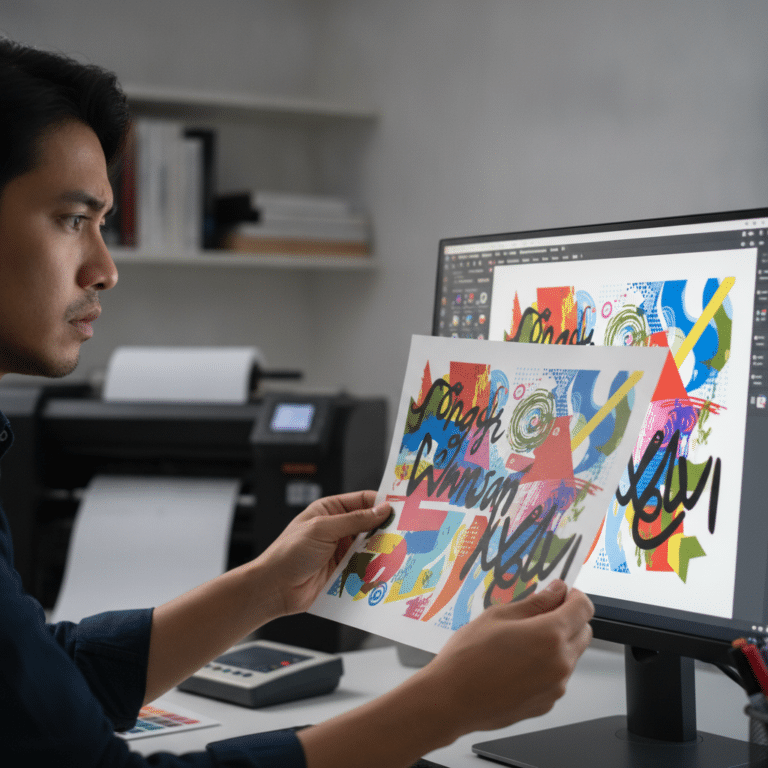
เคล็ดลับเลือกฟอนต์ป้ายโฆษณาให้อ่านง่าย ดึงดูดลูกค้า
การเลือกรูปแบบตัวอักษรหรือฟอนต์สำหรับป้ายโฆษณาเป็นองค์ประกอบที่สำคัญอย่างยิ่งในการสื่อสารกับผู้บริโภค ฟอนต์ที่เหมาะสมไม่เพียงแต่ช่วยให้ข้อความอ่านง่ายและชัดเจน แต่ยังมีบทบาทในการสร้างการรับรู้แบรนด์และดึงดูดความสนใจของลูกค้าเป้าหมาย การตัดสินใจเลือกฟอนต์จึงควรผ่านการพิจารณาอย่างรอบคอบ เพื่อให้ป้ายโฆษณาสามารถทำหน้าที่ได้อย่างเต็มประสิทธิภาพ
สรุปประเด็นสำคัญสำหรับการเลือกฟอนต์
- ความชัดเจนคือหัวใจหลัก: เลือกฟอนต์ที่อ่านง่ายจากระยะไกลและในเวลาอันสั้น โดยเฉพาะฟอนต์ประเภท Sans Serif ที่มีความหนาพอเหมาะ
- จำกัดจำนวนฟอนต์: การใช้ฟอนต์มากเกินไปบนป้ายเดียวทำให้ดูรกและไม่เป็นมืออาชีพ ควรใช้เพียง 1-2 รูปแบบที่เข้ากันได้ดี
- ขนาดมีความสำคัญ: ขนาดของตัวอักษรต้องสัมพันธ์กับระยะการมองเห็น เพื่อให้ผู้ที่สัญจรผ่านไปมาสามารถอ่านข้อมูลสำคัญได้ทันที
- สร้างลำดับชั้นทางสายตา: ใช้ขนาด ความหนา และสีของฟอนต์เพื่อจัดลำดับความสำคัญของข้อมูล ดึงดูดสายตาไปยังหัวข้อหลักก่อน แล้วจึงตามด้วยรายละเอียด
- สอดคล้องกับบุคลิกแบรนด์: ฟอนต์ที่เลือกใช้ควรสะท้อนถึงตัวตนและภาพลักษณ์ของธุรกิจ เพื่อสร้างการจดจำและความน่าเชื่อถือในระยะยาว
สำหรับผู้ประกอบการธุรกิจขนาดกลางและขนาดย่อม (SME) การทำความเข้าใจเกี่ยวกับเคล็ดลับเลือกฟอนต์ป้ายโฆษณาให้อ่านง่าย ดึงดูดลูกค้า ถือเป็นกุญแจสำคัญในการสร้างความได้เปรียบทางการแข่งขัน ป้ายโฆษณาหน้าร้านหรือป้ายไวนิลที่ออกแบบมาอย่างดีสามารถเป็นเครื่องมือทางการตลาดที่ทรงพลัง ทำหน้าที่เชิญชวนลูกค้าให้เข้ามาใช้บริการได้ตลอด 24 ชั่วโมง การเลือกฟอนต์จึงไม่ใช่แค่เรื่องของความสวยงาม แต่เป็นศาสตร์และศิลป์ที่ส่งผลโดยตรงต่อการตัดสินใจซื้อและความสำเร็จของธุรกิจ
บทความนี้จะนำเสนอแนวทางและเทคนิคเชิงลึกในการเลือกฟอนต์สำหรับสื่อสิ่งพิมพ์ประเภทป้ายโฆษณา ตั้งแต่ความสำคัญของฟอนต์ต่อภาพลักษณ์แบรนด์ หลักการเลือกประเภทฟอนต์ที่เหมาะสม ไปจนถึงเทคนิคการจัดวางองค์ประกอบเพื่อให้เกิดประสิทธิภาพสูงสุดในการสื่อสาร ซึ่งจะเป็นประโยชน์ต่อเจ้าของธุรกิจ นักการตลาด และนักออกแบบที่ต้องการสร้างสรรค์ป้ายโฆษณาที่โดดเด่นและบรรลุวัตถุประสงค์ทางการตลาด
ความสำคัญของฟอนต์ต่อการรับรู้แบรนด์
ฟอนต์หรือไทโปกราฟี (Typography) เป็นมากกว่าแค่ตัวอักษรที่เรียงต่อกันเป็นคำ แต่เป็นองค์ประกอบสำคัญในการสร้างอัตลักษณ์ของแบรนด์ (Brand Identity) ในโลกที่เต็มไปด้วยข้อมูลข่าวสาร การมีภาพลักษณ์ที่ชัดเจนและน่าจดจำคือสิ่งจำเป็น ฟอนต์ที่ถูกเลือกอย่างพิถีพิถันจะกลายเป็นเสียงและบุคลิกของแบรนด์ที่สื่อสารกับลูกค้าได้โดยไม่ต้องเอ่ยคำพูด
สร้างการจดจำและความน่าเชื่อถือ
เมื่อผู้บริโภคเห็นฟอนต์ที่ใช้เป็นประจำในทุกสื่อของแบรนด์ ไม่ว่าจะเป็นบนป้ายโฆษณา นามบัตร หรือเว็บไซต์ จะเกิดการเชื่อมโยงและการจดจำโดยไม่รู้ตัว ฟอนต์ที่ดูเป็นมืออาชีพ สะอาดตา และเหมาะสมกับประเภทธุรกิจ จะช่วยเสริมสร้างความน่าเชื่อถือและความไว้วางใจให้กับลูกค้าได้เป็นอย่างดี ในทางกลับกัน ฟอนต์ที่อ่านยากหรือไม่สอดคล้องกับภาพลักษณ์ อาจสร้างความรู้สึกสับสนและลดทอนความเชื่อมั่นที่มีต่อแบรนด์
สื่อสารบุคลิกของแบรนด์
ฟอนต์แต่ละรูปแบบมีลักษณะเฉพาะตัวที่สามารถกระตุ้นอารมณ์และความรู้สึกที่แตกต่างกันได้ ตัวอย่างเช่น:
- ฟอนต์ที่มีความหนาและแข็งแรง อาจสื่อถึงความมั่นคง ความน่าเชื่อถือ เหมาะสำหรับธุรกิจการเงินหรือก่อสร้าง
- ฟอนต์ที่ดูโค้งมนและเป็นมิตร อาจสื่อถึงความอ่อนโยน การเข้าถึงง่าย เหมาะสำหรับสินค้าสำหรับเด็กหรือธุรกิจบริการ
- ฟอนต์ที่ดูหรูหราและมีเชิง (Serif) อาจสื่อถึงความคลาสสิก ประสบการณ์ที่ยาวนาน เหมาะสำหรับแบรนด์สินค้าลักซ์ชัวรีหรือธุรกิจที่มีประวัติศาสตร์
การเลือกฟอนต์ที่สอดคล้องกับบุคลิกของแบรนด์จึงเป็นการตอกย้ำจุดยืนและคุณค่าของธุรกิจให้ชัดเจนยิ่งขึ้น
หลักการพื้นฐานในการเลือกฟอนต์สำหรับป้ายโฆษณา
การออกแบบป้ายโฆษณาที่มีประสิทธิภาพต้องยึดหลักความเรียบง่ายและชัดเจนเป็นสำคัญ การเลือกฟอนต์ก็เช่นเดียวกัน การทำความเข้าใจหลักการพื้นฐานจะช่วยให้การตัดสินใจง่ายขึ้นและได้ผลลัพธ์ที่ดี
จำกัดจำนวนฟอนต์: น้อยแต่มาก
หนึ่งในข้อผิดพลาดที่พบบ่อยที่สุดในการออกแบบป้ายหน้าร้านคือการใช้ฟอนต์หลากหลายรูปแบบมากเกินไป ซึ่งทำให้ป้ายดูสับสน ขาดความเป็นเอกภาพ และลดทอนความเป็นมืออาชีพ แนวทางปฏิบัติที่ดีที่สุดคือการจำกัดการใช้ฟอนต์ไว้ที่ 1-2 รูปแบบต่อหนึ่งชิ้นงาน
โดยอาจเลือกฟอนต์หนึ่งสำหรับหัวข้อหลัก (Headline) เพื่อดึงดูดความสนใจ และอีกฟอนต์หนึ่งสำหรับเนื้อหารายละเอียด (Body Text) ที่เน้นการอ่านง่าย หากต้องการสร้างความแตกต่าง สามารถใช้วิธีปรับเปลี่ยนน้ำหนัก (เช่น ตัวหนา ตัวบาง) หรือขนาดของฟอนต์เดียวกันแทนการเพิ่มฟอนต์ใหม่เข้ามา
การจับคู่ฟอนต์อย่างมีศิลปะ
หากตัดสินใจใช้ฟอนต์สองรูปแบบ ควรเลือกฟอนต์ที่มีความแตกต่างกันอย่างชัดเจนแต่ยังคงความเข้ากันได้ (Contrast and Harmony) เพื่อสร้างลำดับชั้นทางสายตาและทำให้การออกแบบดูน่าสนใจยิ่งขึ้น เช่น การจับคู่ฟอนต์แบบ Sans Serif ที่ดูทันสมัยสำหรับหัวข้อ กับฟอนต์ Serif ที่ดูคลาสสิกสำหรับเนื้อหาย่อย หรือการใช้ฟอนต์ที่มีน้ำหนักต่างกันอย่างชัดเจน
ประเภทของฟอนต์: เลือกอย่างไรให้เหมาะสม
ฟอนต์สามารถแบ่งออกได้เป็นหลายประเภท แต่สำหรับงานป้ายโฆษณา การทำความเข้าใจความแตกต่างระหว่างประเภทหลักๆ จะช่วยให้เลือกใช้งานได้อย่างเหมาะสม